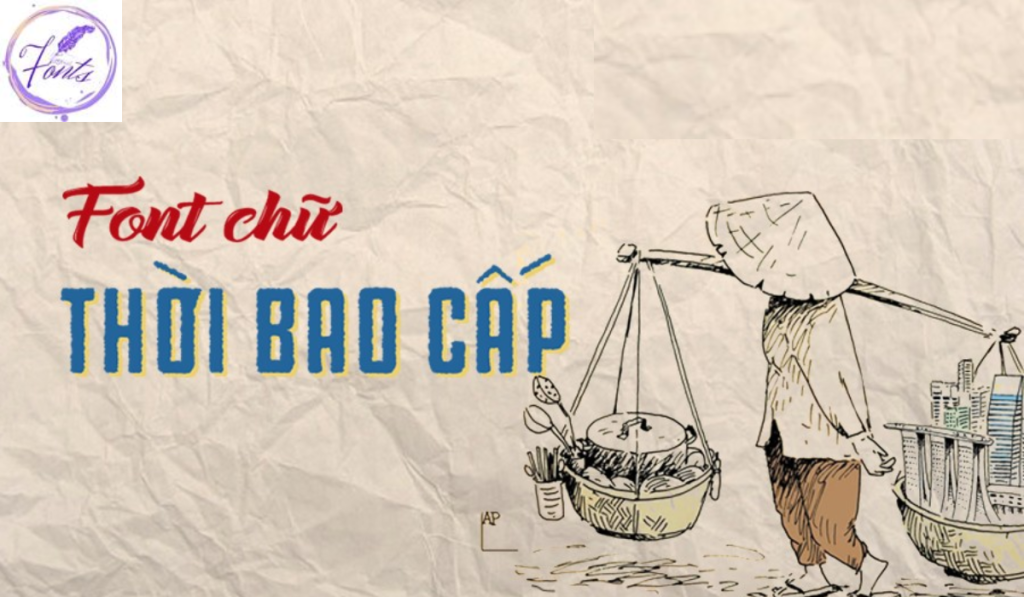
Font chữ thời bao cấp
Tác giả: Tống Văn Hiệp
Bộ Font: Bia Sach Xua
Phân loại: Retro, hoài cổ
Kiểu chữ: Có chân, không chân, viết tay
Độ dày: Light, Regular, Medium, Bold, Black
Đánh giá font chữ thời bao cấp
Bộ sưu tập font chữ thời bao cấp của vietfontz.com đã nhận được sự đánh giá cao từ cộng đồng thiết kế đồ họa và chuyên gia typography. Với sự kết hợp hoàn hảo giữa tính thẩm mỹ và tính ứng dụng, các font bao cấp của chúng tôi đã được sử dụng rộng rãi trong nhiều lĩnh vực như thiết kế logo retro, bao bì sản phẩm hoài cổ, thiệp mời sự kiện với chủ đề về thời bao cấp. Nhiều khách hàng đã gửi phản hồi tích cực về chất lượng và sự đa dạng của bộ sưu tập font chữ thời bao cấp, đồng thời đánh giá cao sự hỗ trợ nhiệt tình của đội ngũ chúng tôi. Với vietfontz.com, bạn có thể hoàn toàn yên tâm về chất lượng và sự hài lòng khi sử dụng font chữ bao cấp.